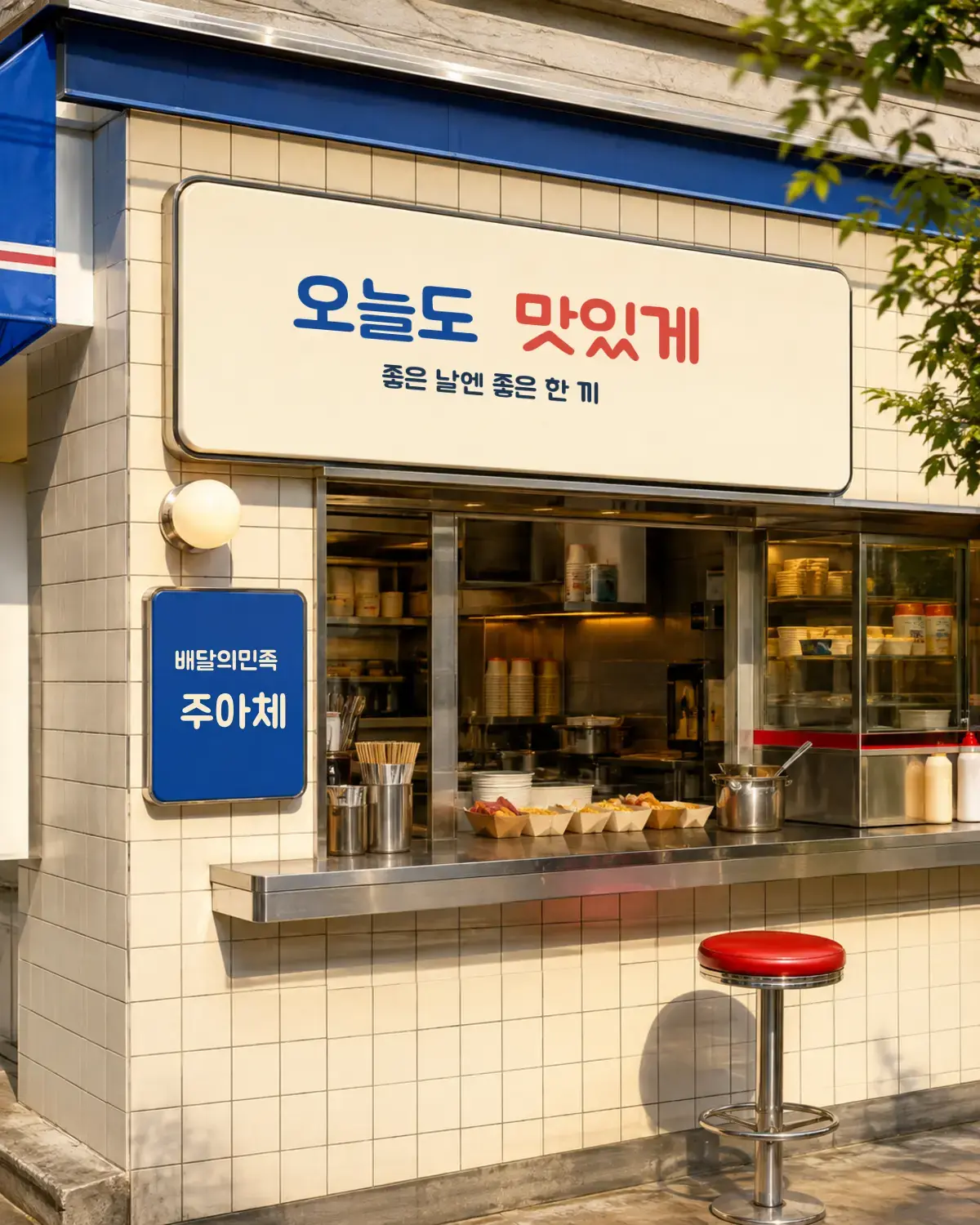
배달의민족 주아체 — 우아한형제들에서 배포하는 무료 폰트입니다. 붓으로 직접 그린 옛 간판 글씨에서 온 서체로, 획 굵기가 들쭉날쭉해 정겨운 인상을 주는 제목용 서체
우아한형제들이 2014년에 내놓은 배민 서체 시리즈의 두 번째 작품입니다. 산돌커뮤니케이션이 제작에 함께했습니다.
시리즈 안에서 이 서체의 자리를 알면 이해가 빠릅니다. 배민 서체들은 저마다 다른 간판을 모티브로 삼는데, 한나체가 아크릴 판에 시트지를 붙여 칼로 잘라낸 간판이라면 주아체는 붓으로 직접 그린 손글씨 간판입니다. 제작사 설명 그대로, 붓으로 그려 획의 굵기가 일정하지 않고 동글동글한 느낌을 주며 옛날 간판의 푸근함과 정겨움이 묻어나는 것이 특징입니다.